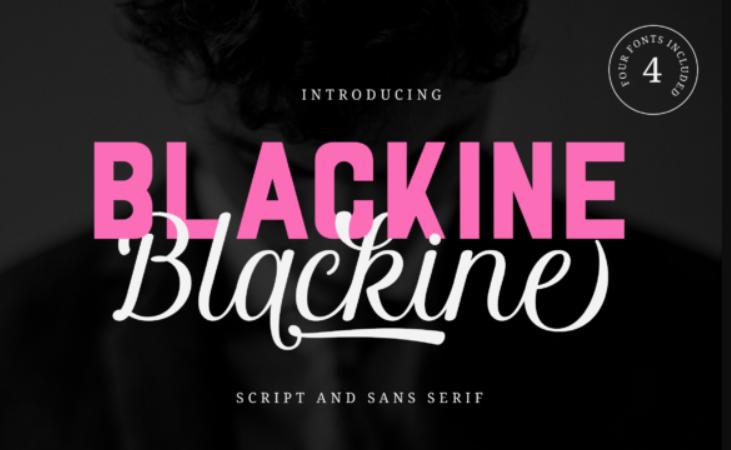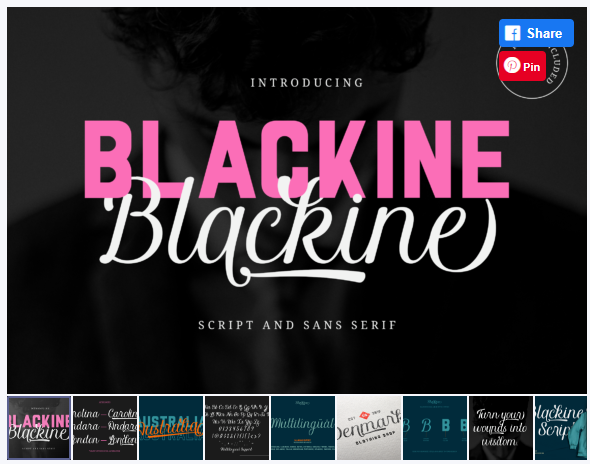
[Creativefabrica] Blackine Font (ahweproject)
Blackline - это винтажный двойной шрифт (без засечек и засечек). Тщательно созданный, чтобы добиться хорошего тона и очаровательного результата, этот шрифт можно смешивать, чтобы создавать уникальные идеи, которые отражают старый, но современный стиль!